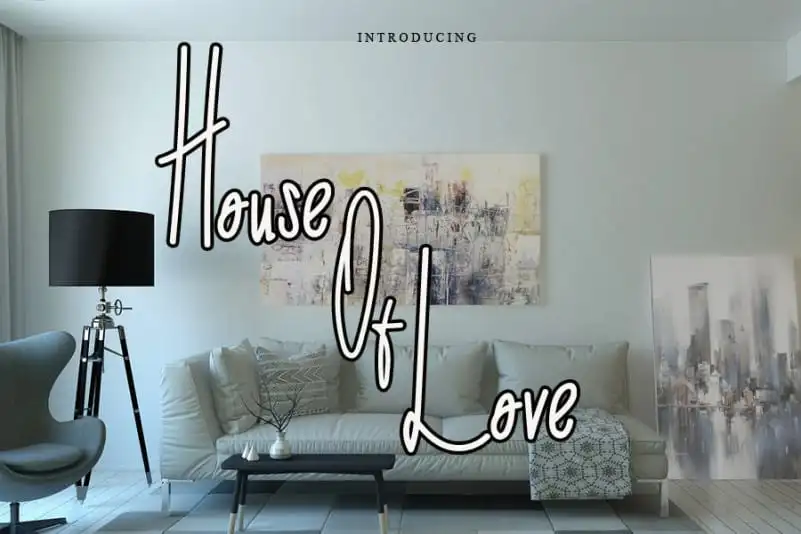
House of Love Handwritten Font – Download Grátis
A House of Love Handwritten Font é uma fonte escrita a mão com um estilo elegante e delicado, perfeita para adicionar um toque singelo e sofisticado aos seus projetos design. Com sua aparência limpa, fina e suave, essa fonte será uma ótima opção para aqueles que procuram uma escolha versátil para o seu próximo projeto gráfico. Seja para criar cartões de aniversário, editoriais de revistas ou até mesmo para adicionar um toque pessoal em sua identidade visual empresarial, a House of Love Handwritten Font oferece uma variedade de opções que se adequam perfeitamente. Estamos certos de que ela será bem-vinda para complementar qualquer projeto design criado por você.